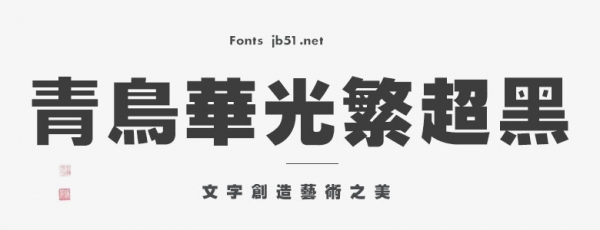
青鳥(niǎo)華光繁超黑
青鳥(niǎo)華光繁超黑是一款應(yīng)用于設(shè)計(jì)方面的簡(jiǎn)體中文漢字,該字體線條粗壯有力,字形大方得體,整體效果出眾,并且字庫(kù)完整,可用于藝術(shù)設(shè)計(jì)、包裝印刷、簽名設(shè)計(jì)、圖形設(shè)計(jì)等領(lǐng)域,有需要的朋友可以免費(fèi)下載收藏。